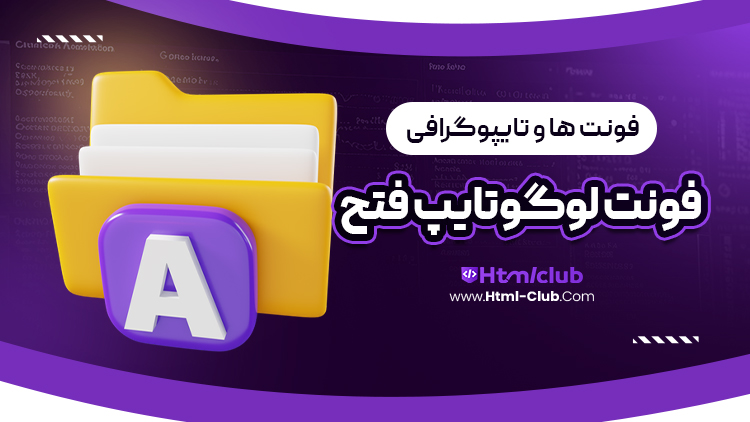
فونت لوگوتایپ فتح در سایت html club برای شما عزیزان قرار داده شده است.فونت لوگوتایپ “فتح” یکی از فونت‌های جذاب و مدرن در طراحی گرافیک فارسی است که به‌ویژه در زمینه برندینگ و تبلیغات مورد توجه قرار گرفته است. این فونت با طراحی خاص و منحصر به فرد خود، توانسته است جایگاه ویژه‌ای در میان طراحان و برندها پیدا کند. در این متن به بررسی ویژگی‌ها، کاربردها، مزایا و اهمیت فونت لوگوتایپ فتح می‌پردازیم.
ویژگی های برجسته فونت لوگوتایپ فتح:
نوآوری در طراحی
فونت فتح به راحتی با سبک‌های مختلف طراحی هماهنگ می‌شود و این امکان را به طراحان می‌دهد که از آن در پروژه‌های متنوع استفاده کنند.
تنوع کاربرد
یکی از اصلی‌ترین کاربردهای فونت فتح، استفاده در طراحی لوگوهاست. این فونت می‌تواند هویت بصری قوی برای برندها ایجاد کند.
شخصیت منحصر به فرد
فونت فتح با خطوط نرم و متوازن خود، ظاهری مدرن و شیک دارد. طراحی آن به گونه‌ای است که به راحتی می‌تواند توجه مخاطبان را جلب کند.
پشتیبانی از زبان های مختلف
هنچین یکی از مهم ترین مزایای این لوگوتایپ این است که به خوبی از تمام حروف دو زبان عربی و فارسی پشتیبانی میکند.